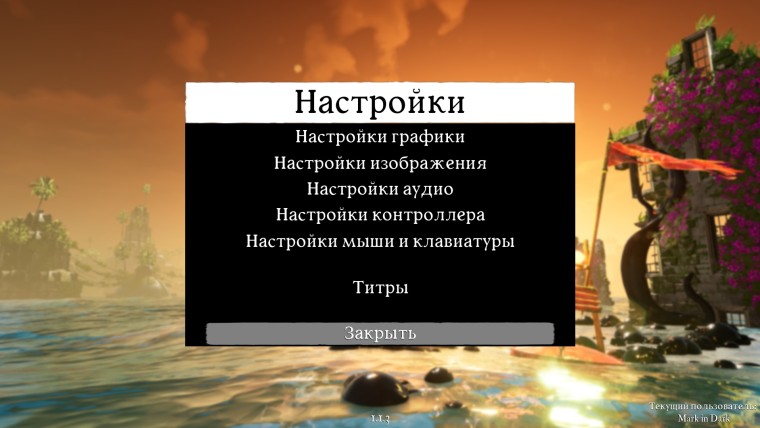
Исправленный русский шрифт для игры Submerged: Hidden Depths, заменяющий стандартный по умолчанию. Шрифт более стилизован под оригинальный в отличие от официального варианта. Подходит для всех версии игры.